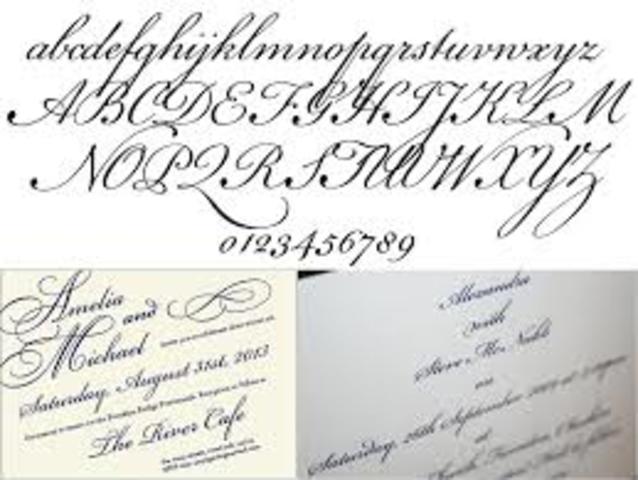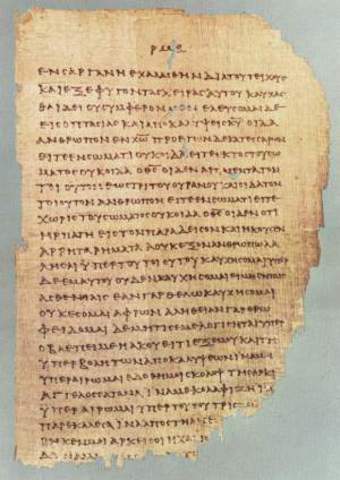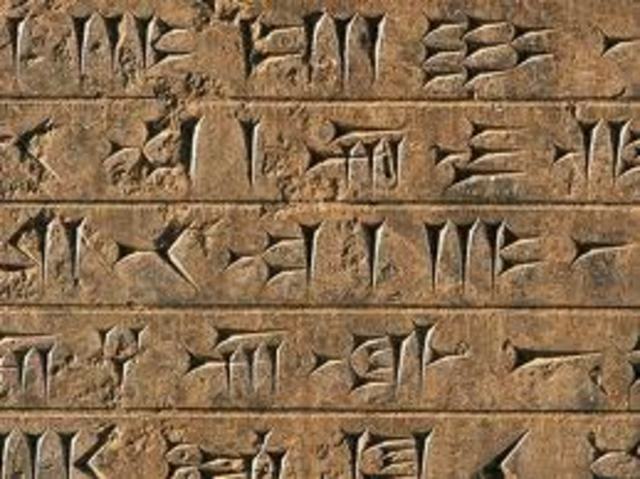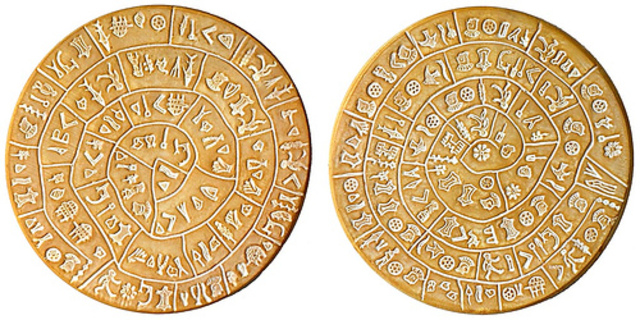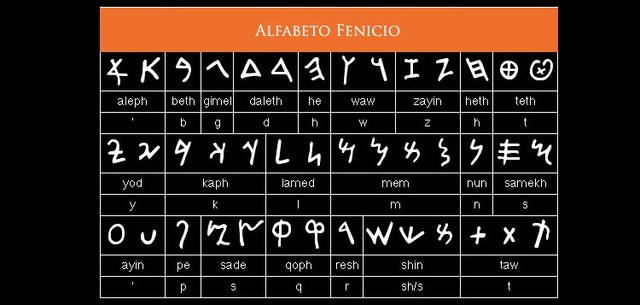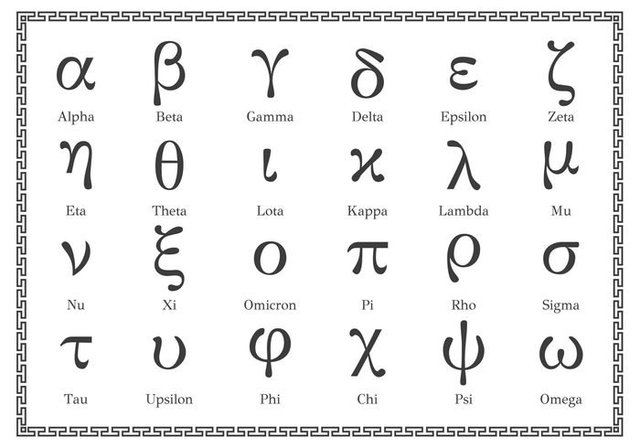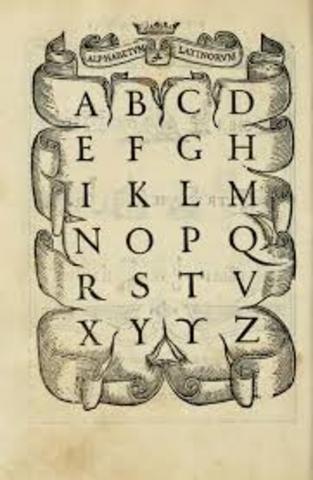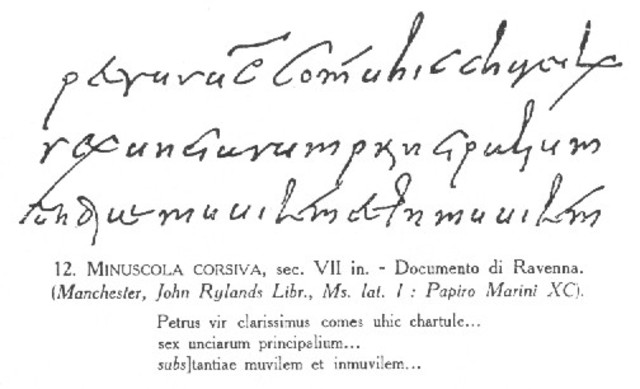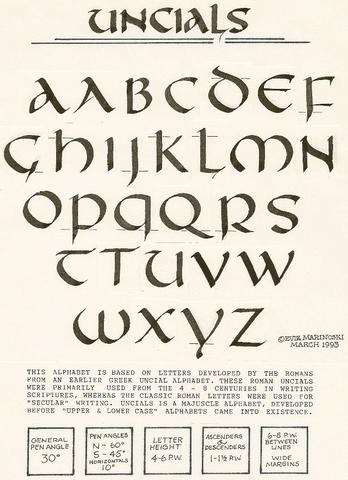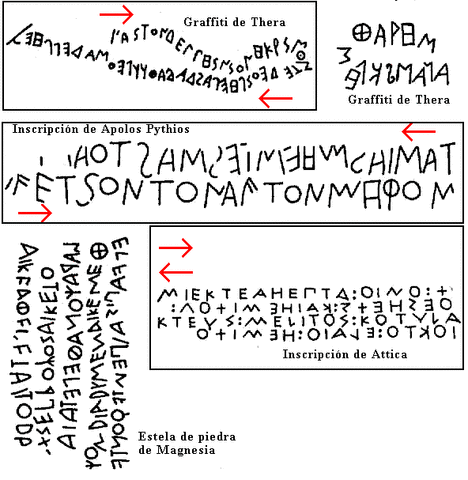
Tipografia
TIPOGRAFÍA DESDE GRECIA AL SIGLO XIV por: NODIER CAMILO VALLEJO
• INVENTO DE LA IMPRENTA Y TIPOGRAFÍA MÓVIL
1440 BCE
INVENTO DE LA IMPRENTA Y TIPOGRAFÍA MÓVIL
• USO DE LA XILOGRAFA Y TIPOGRAFÍA
1300 BCE
USO DE LA XILOGRAFA Y TIPOGRAFÍA
• LA UNCIAL
1201 BCE
LA UNCIAL
Tipo de escritura en el cual todo el texto se escribe en mayúscula.
• ESCRITURA CURSIVA ROMANA NUEVA
300
ESCRITURA CURSIVA ROMANA NUEVA
También llamada minúscula cursiva o cursiva romana final.
• LA ESCRITURA
500
LA ESCRITURA
Los griegos prefieren la escritura de izquierda a derecha a diferencia de las demás lenguas.
• MANUSCRITO ILUMINADO
600
MANUSCRITO ILUMINADO
Texto complementado con una decoración.
• ALFABETO LATINO
700
ALFABETO LATINO
Los latinos adoptaron las variantes del alfabeto griego, de la colonia de cumas, que contaba con 21 letras pero finalmente los latinos dejaron 26.
• ALFABETO GRIEGO
800
ALFABETO GRIEGO
Se desarrollo tomando como base el alfabeto fenicio
• ALFABETO FENICIO
1000
ALFABETO FENICIO
Los griegos perfeccionaron el alfabeto fenicio, añadiendo signos para las vocales (inexistentes en los alfabetos de origen semita) hasta un total de 23 o 24 caracteres.
• Period: to 1000
APARICIÓN DE DISTINTOS ALFABETOS
SEMÍTICOS: Derivados del fenicio
• PICTOGRAMA CRETENCE
PICTOGRAMA CRETENCE
Primeras apariciones del alfabeto
• USO DE LA ESCRITURA CUNEIFORME
USO DE LA ESCRITURA CUNEIFORME
• PAPIRO E ILUSTRACIONES COMO SOPORTE DE ESCRITURA
PAPIRO E ILUSTRACIONES COMO SOPORTE DE ESCRITURA
• EL USO DE LOS PICTOGRAMAS
EL USO DE LOS PICTOGRAMAS